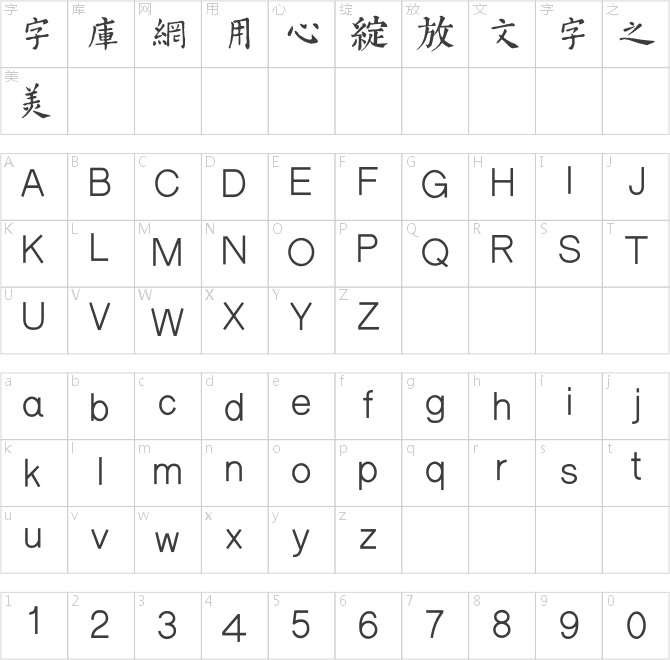
字体名称: 邯郸欧阳询千字
作者版权: 韩绍杰
邯郸欧阳询千字文
注:本字库为古籍千字文复刻书法小字库,字符数量为1000余字,如有特殊需求,可以联系邯郸字库韩绍杰为您订制,也可以联系本站客服为您转答!
欧阳询(557年—641年),字信本,汉族,唐朝潭州临湘(今湖南长沙)人,唐朝著名书法家、官员,楷书四大家之一。南梁征南大将军欧阳頠之孙,南陈左卫将军欧阳纥之子,南朝梁太平二年(公元557年)出生于衡州(今湖南衡阳),祖籍潭州临湘(今湖南长沙)。 欧阳询与同代的虞世南、褚遂良、薛稷三位并称初唐四大家。因其子欧阳通亦通善书法,故其又称“大欧”。 欧阳询与虞世南俱以书法驰名初唐,并称“欧虞”,后人以其书于平正中见险绝,最便于初学者,号为“欧体”。
邯郸欧阳询千字文字体字库是一款让人赏心悦目、百看不厌的中文字体,适合各类广告和产品包装设计应用,字体大小6.56MB,格式为ttf字体,上传用户是邯郸字库,作者/版权方为韩绍杰